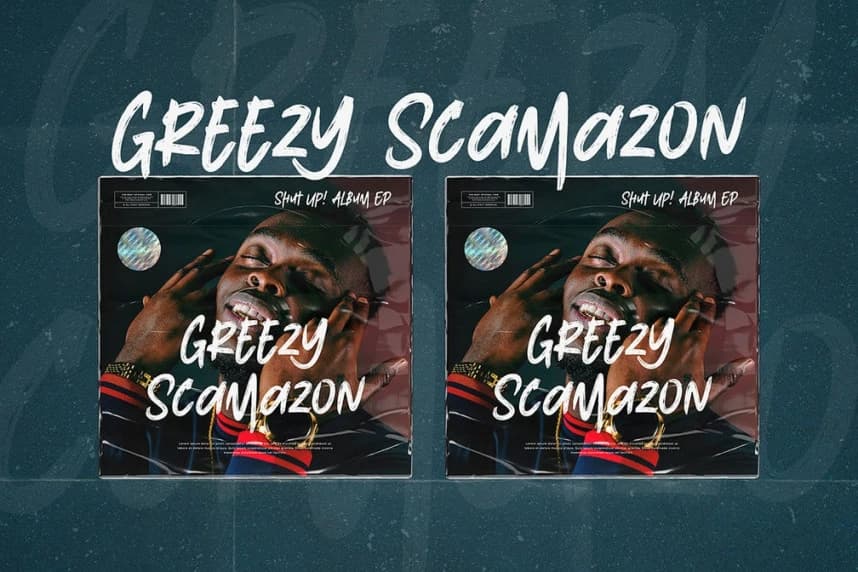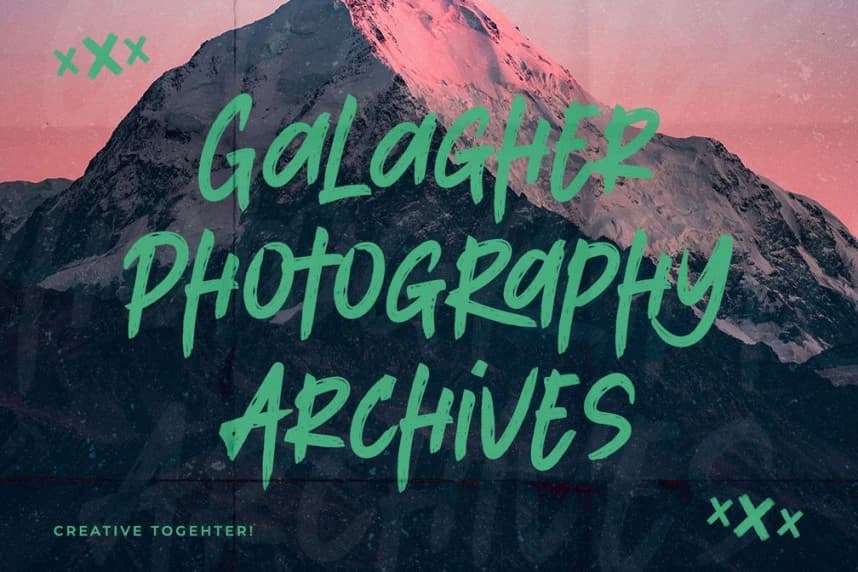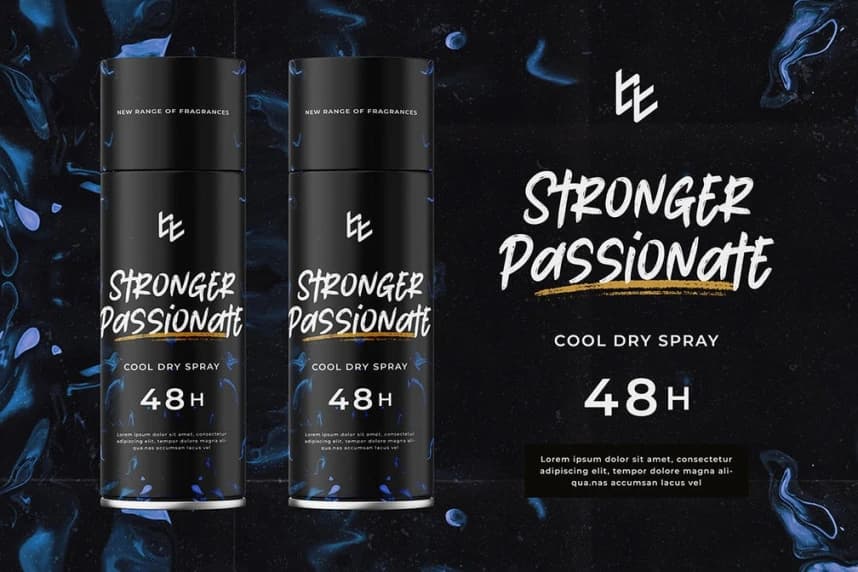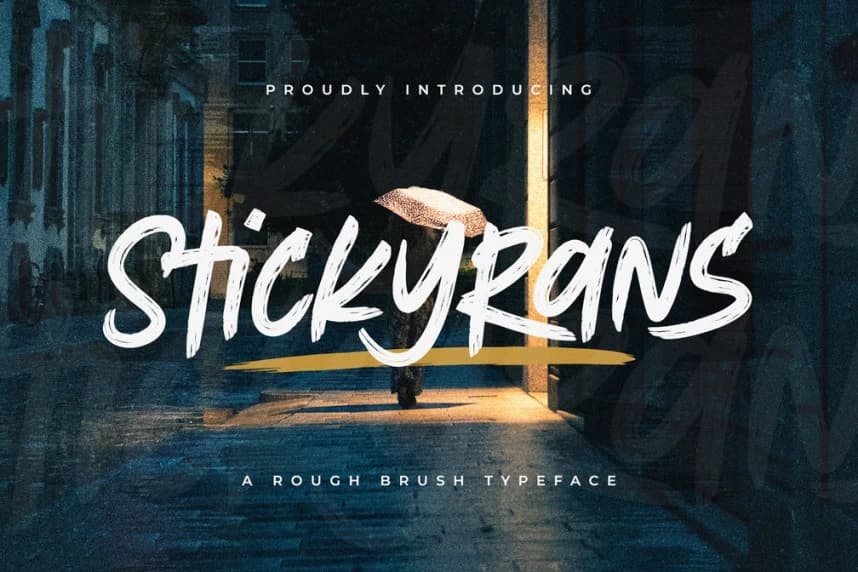
Stickyrans Brush Font
Stickyrans Brush Font – tasarımlarınıza otantik bir hava katan pürüzlü bir fırça tipi yazı tipidir! Dokulu ve ifade dolu harf biçimleriyle, “Stickyrans” ham yaratıcılığın özünü yakalar. Her karakter, cesur bir dengeyi en iyi şekilde yansıtacak biçimde özenle tasarlandı.
Stickyrans Brush Font – tasarımınıza özgün bir dokunuş katan kaba bir fırça tipografisi! Pürüzlü ve ifade dolu harf formlarıyla, “Stickyrans” ham yaratıcılığın özünü yakalar. Her karakter, cesur bir dengeyi sergilemek için titizlikle tasarlanmıştır.